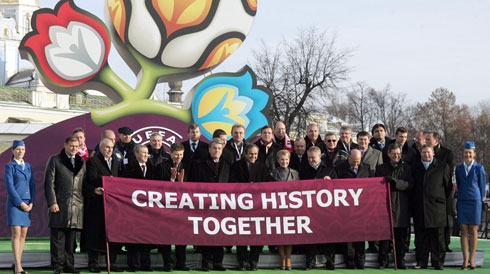
Ein Blütenlogo für die UEFA EURO 2012
In Kiew wurden vor wenigen Minuten das offizielle Signet, das Corporate Design und der Slogan für die Fußball-Europameisterschaft 2012 in Polen und der Ukraine vorgestellt. Die beiden Gastgeber wollen »Zusammen Geschichte schreiben«, so das Motto des Turniers. Höhepunkt der Zeremonie war die Enthüllung des Logos vom Präsidenten des Polnischen Fußballverbands, Grzegorz Lato, seinem ukrainischen Amtskollegen Grigoriy Surkis und UEFA-Präsident Michel Platini.
In der offiziellen Verlautbarung der Veranstalters UEFA heißt es: »Mit dem Logo möchte man der UEFA EURO 2012™ eine eigene Persönlichkeit geben. Die visuelle Identität wird sich auch auf Promo-Artikeln, den Eintrittskarten und Internet-Bannern wiederfinden. Ziel ist es, das Turnier – welches zu den größten Sportereignissen der Welt zählt – weiter zu vermarkten und es mit einem Wiedererkennungswert zu versehen.«
Bei der Konzipierung des Logos wurde darauf geachtet, dass die Gastgeber darin fest verankert sind und so orientierte man sich am »wycinanka«, einer traditionellen Art Schnittbilder aus Papier herzustellen, wie es vor allem in den ländlichen Gegenden in Polen und der Ukraine geschieht. Damit soll auch die Tier- und Pflanzenwelt der Region gewürdigt werden. Das Logo besteht aus zwei Blüten, die jeweils eine Gastgebernation repräsentieren, und einem Ball in zentraler Position zur Verdeutlichung der Emotion und der Leidenschaft, die der Wettbewerb mit sich bringt. Der Stiel kennzeichnet den strukturellen Aspekt des Turniers, also die UEFA und den europäischen Fußball. Die Natur diente auch als Inspiration für weitere Eigenschaften des CI, so steht grün für die Waldgebiete, gelb für die Sonne, blau für das Wasser und den Himmel.
Das 2-minütige UEFA-Video »The Brand Story« verrät mehr über die Typografie, Farbgebung und das Zusammenspiel der Formen im Corporate Design der Fußball EM 2012:
Das Motto der Europameisterschaft lautet »Zusammen Geschichte schreiben«. Die Austragung der UEFA-Europameisterschaft in Polen und der Ukraine hat einen Eintrag in den Geschichtsbüchern sicher, weil noch nie zuvor ein Turnier in Zentral- und Osteuropa durchgeführt wurde.
Sieht ja auch so ‘n bisschen aus wie ‘n Torwart. Bundesgartenschau der FIFA, auch schön.
Irgendwie zu komplex, zu wenig Fußball, zu sehr niedlich. Aber schön. Als Illustration gut, aber als Logo ein wenig übers Ziel hinaus.
Also, da denk ich dran, wie man mit Fußballspielen Nachbarinnens Blumenbeete verwüstet.
ich finde es im kontext unheimlich frisch und gelungen. die metapher mit der ranke und fussball als wachstumschance, und den stadien als blüten der auflebenden ereignisse. herrlich verspielt :) die typo wirkt dagegen noch etwas zu steril, sowas ähnliches wie in der scribblephase im video hätte ich besser gefunden.
eigentlich ist die idee ja ganz nett, ein logo als eine art bauernmalerei in diesem typischen blumendesign. bei 0:25 sieht man diese originalen blumenschnittbilder, wie man sie aus den osteuropäischen ländern kennt. allerdings finde ich die umsetzung mit farbverläufen und 3d-effekten weniger ansprechend, der typische charakter dieser 2d-blumen kommt da einfach nicht rüber. weniger kitschiges kaugummidesign, dafür mehr illustration und klassisches 2d hätte mir persönlich besser gefallen. aber die osteuropäischen länder sind ja für ihre knallbunten farben bekannt, ich sage nur ‘Eurovision Song Contest’ – fußball + wiese/rasen klappt ja auch irgendwie, von daher: passt schon.
die RO-ligatur erschließt sich mir nicht ganz. bei so einem bunten logo sollte man den schriftzug nicht auch noch übergestalten.
idee gut, video gut, logo auch aber das RO mag mir weder einleuchten noch gefallen. wie mein vorredner bereits geschrieben, einfach zu viel zumal Sinn nicht ersichtlich.
Wäre die EM in Holland würde das Logo deutlich besser passen.
Denn ich verbinde weder Polen noch die Ukraine in irgendeiner Form mit Blumen….
till1
christopher: aber liegt das an polen und der ukraine, oder daran, dass wir nicht soviel über deren kulturen wissen?
Janni
Mir gefällts ausgesprochen gut: Hier und da ist es etwas überbordend und auch nicht unbedingt perfektionistisch – aber das ist doch irgendwo auch ziemlich typisch für “osteuropäisches” (OK, ich verallgemeinere) Design. Der Trailer jedenfalls hat mich über weite Strecken sehr an das erinnert, was ich bisher mit polnischer Grafik verbunden habe. Das ist doch schonmal viel Wert und macht Lust auf mehr – im Unterschied zu all den anderen trostlosen Logos und Erscheinungsbildern zu Sportgroßereignissen der letzten Jahre.
Eckhard
Manchmal wäre es besser, man würde die Begründung des Logos nicht lesen. Lese ich da wirklich richtig?
“so steht grün für die Waldgebiete, gelb für die Sonne, blau für das Wasser und den Himmel.”
Was für ein Ding: Polen und die Ukraine haben grünen Wald, gelbe Sonne und blauen Himmel, nebst blauem Wasser. Das sind schon Gründe, Geschichte zu schreiben.
Wo wird in dem Logo, wie erwähnt, die Tierwelt gewürdigt? Oder ist der Ball im Osten ein kleines putziges Waldtierchen?
Ne 2D Lösung hätte mich wahrscheinlich mehr angesprochen.
Vielleicht möchte man ja zeigen, dass man mit “moderner”
Effekthascherei dem Westen in nichts nachsteht.
Was laber ich da eigentlich ;)…. das Zeichen sieht ja trotzdem ganz
ansehnlich aus.
auch für ein kurzfristig eingesetztes Aktionszeichen immer noch etwas zu viel Schatten und Kneteoptik, aber schön schwülstig und mit 37 Inhaltsebenen alles andere als schmallippig. Ich kenne mich mit Fußball überhaupt nicht aus, aber die Formensprache ist für mich nicht Fußball, eher die einer Spielemesse.